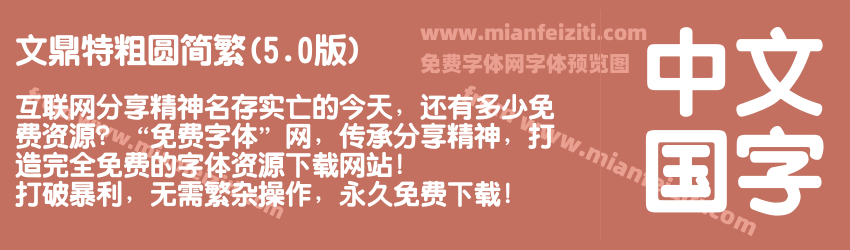
文鼎特粗圆简繁(5.0版)
更新Power TrueType Version 5.0版,和原Power TrueType Version 4.0或Power TrueType Version 4.5版本相比又将原Power TrueType big5的扩展471个外字集的部分没有映射字码点的汉字进行了对号入座,并修复『㘭』字误映射到『抝』字位置的错误。
本款“文鼎特粗圆简繁(5.0版)”是一款书写很新颖的字体,字体大方,适合各种设计作品使用!欢迎下载!